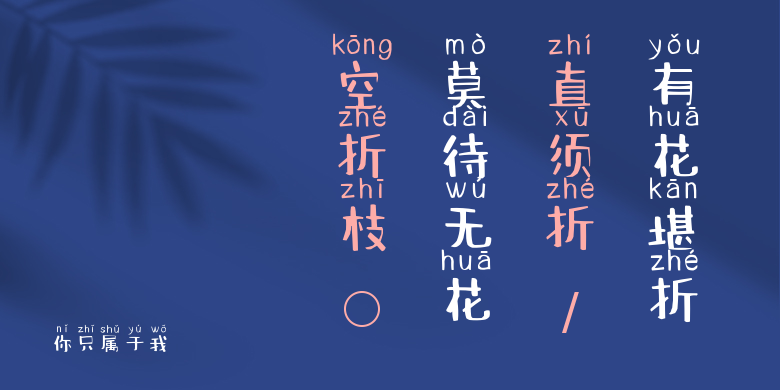
你只属于我
你只属于我,这款字体结构工整、笔画清晰,兼顾美观与易读性,适用于标题、正文、海报、包装、LOGO 等多种场景。字形优雅稳定,风格百搭耐看,适配日常排版与创意设计,让文字呈现更舒适、更具质感。你只属于我一笔一画,皆是细节,以均衡的比例、流畅的线条打造舒适视觉体验,字形端正大气,风格简约现代。无论是商业设计、品牌宣传还是日常排版,都能轻松驾驭,让文字更有格调与力量。你只属于我字体下载。